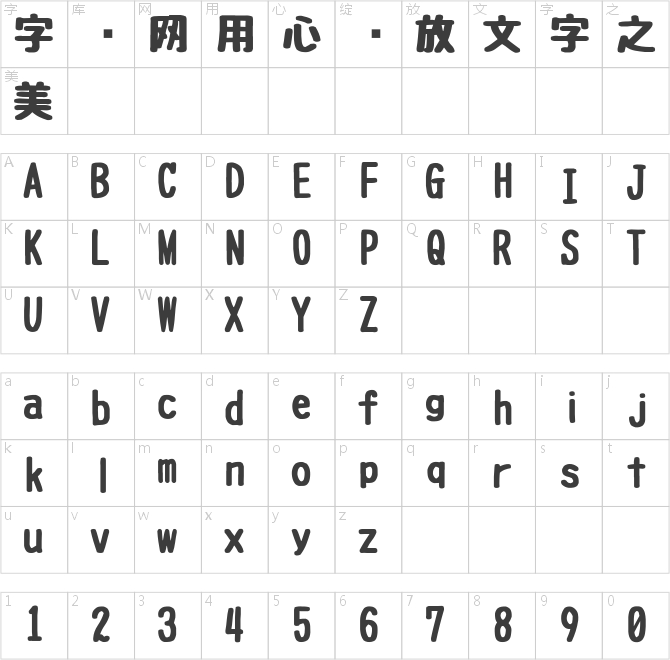
字體名稱: 自由字體
自由字體
自由字體介紹
自由字體字體下載Jiyucho
自由字體是自由的圓形文字風格的手寫字體。像用粗一點的簽字筆寫的那樣,以溫暖的黑體為目標而制作的。自由字體因為筆畫較粗,特別適合用于標題的設計。既有黑體的特征,又比黑體多了一分手寫的痕跡。這款字體我十分喜歡,因為他夠粗,如果能有多一點的簡體字就好了。
這款字體包含簡體中文字體4402個,其中常用字2470個。
自由字體效果圖